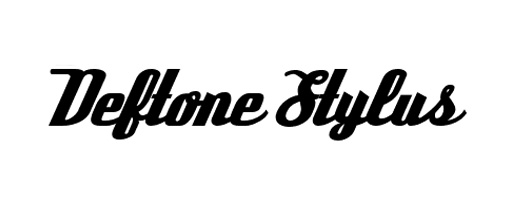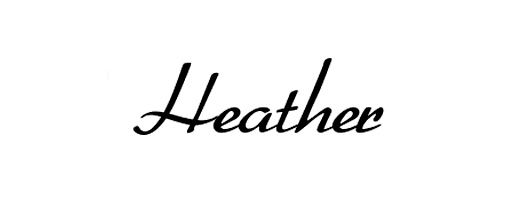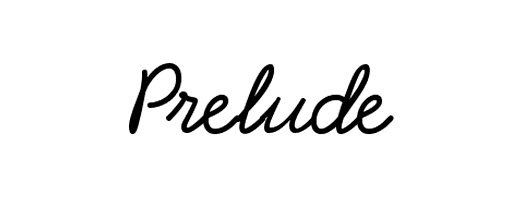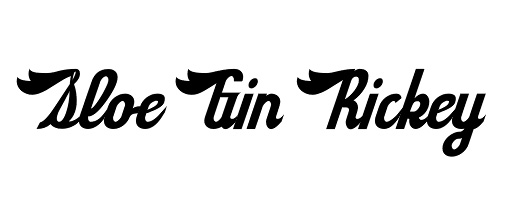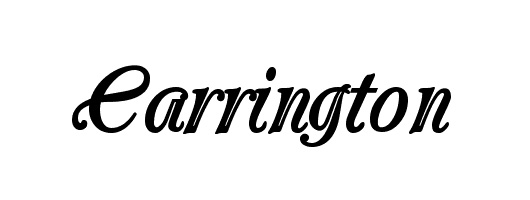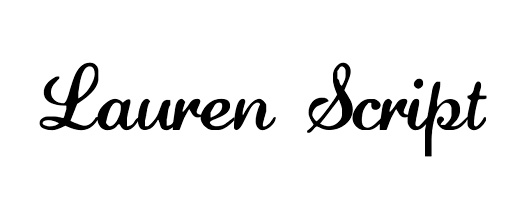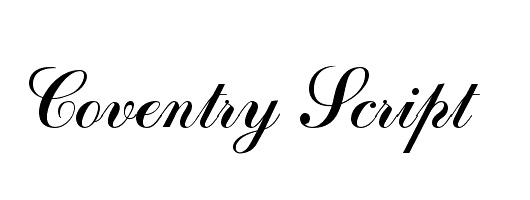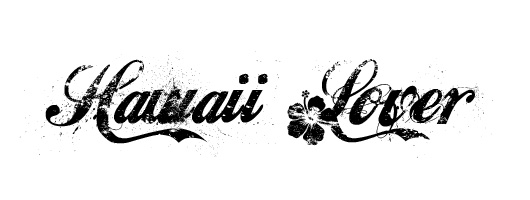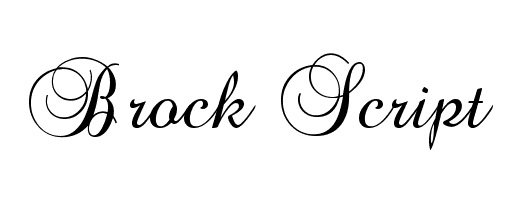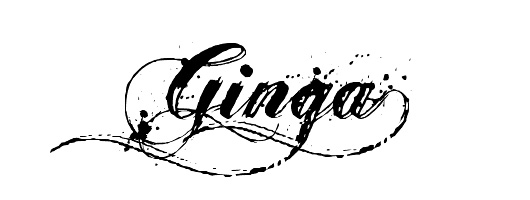
Schreibschriften, ob klassisch, modern oder extravagant kann man prima in Webdesigns verwenden, um dem Design einen individuellen Touch zu verleihen. Da es unendlich viele Free-Fonts gibt ist es nicht immer einfach, schnell eine passende Schrift zu finden. Daher habe ich meine 20 Lieblings Schreibschrift Free-Fonts für dich zusammen gestellt.
1. Marketing Script
2. Creampuff
3. Learning Curve Pro
4. Ballpark
5. Deftone Stylus
6. BlackJack
7. Heather
8. Miama
9. Magesta Script Mix
10. Prelude
11. Sloe Gin Rickey
12. Black Rose
13. The King & Queen Font
14. Adorable
15. Carrington
16. Lauren Script
17. Coventry Script
18. Hawaii Lover
19. Brock Script
20. Ginga
Ginga und Hawaii Lover sind wirklich sehr schön, kann man bestimmt mal verwenden.
Ich finde genau wie Andreas die Hawaii Lover auch echt spitze,
mal schauen wo man die verwenden kann :)
Auch mir gefällt Hawaii Lover sehr gut. Und ich hätte auch nichts dagegen, jetzt in Hawaii am Strand zu liegen :) The King & Queen finde ich auch sehr schön. Ich finde es immer wieder toll, neue kreative Fonts zu entdecken und damit Webseiten zu verschönern :)
@wordweb ;-) lying on the beach sounds great :) und the King and Queen Typeface finde ich auch echt klasse.
Die passende Schrift für die Karte ist mir hier schon sehr positiv aufgefallen (Nr. 7) – sie ist wirklich sehr schön!!!
Ich kann die Schriftart Ginga nur weiter empfehlen.
Ich bin regelrecht begeistert von diesen schönen Schriften!